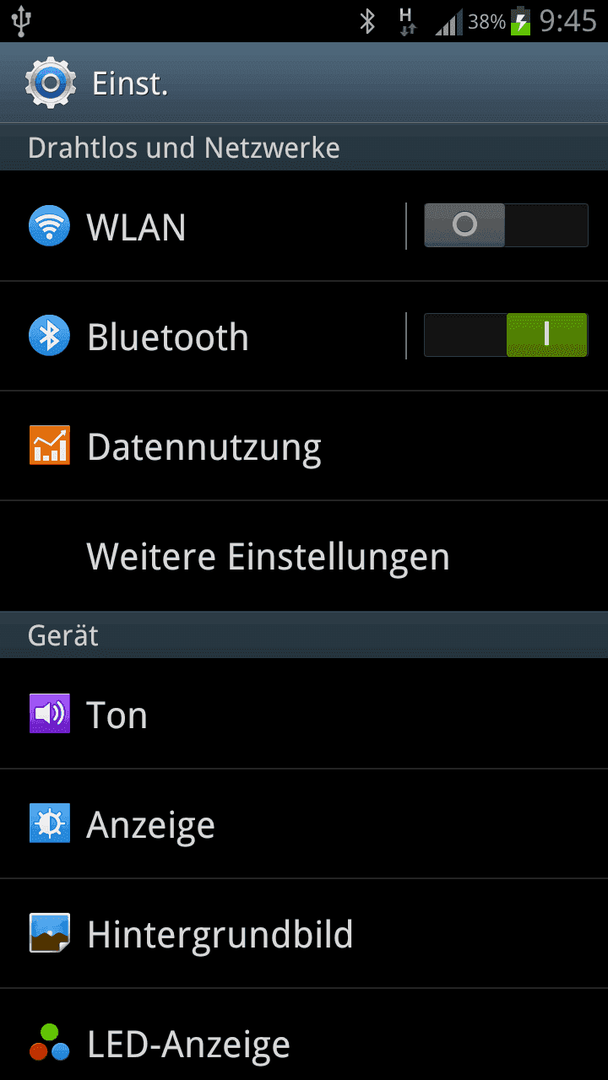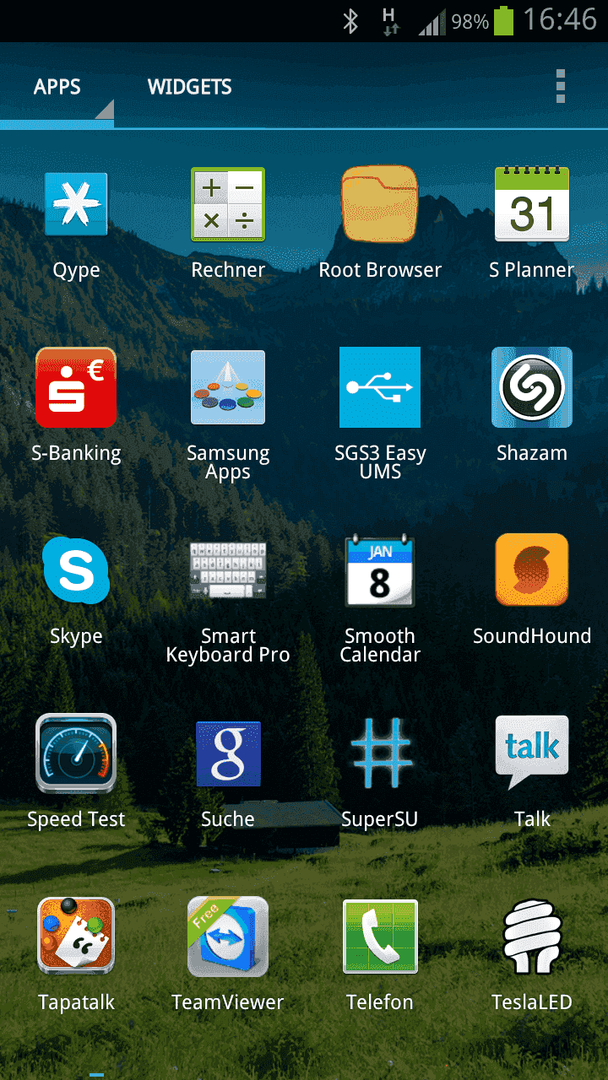
Schriftart (~Font) ändern
Ich erkenne dort keinen Unterschied.
Zwischen dem StockFont & dem Font.
Oder Täusche ich mich etwa?
Ich sehe auch keinen Unterschied.:confused:
Zumal das andere was angeboten wird (CheckROM) viel hübscher ist ^^
Was meinst Du mit "das andere"?
Aber ob hübscher oder nicht ist ja bekanntlich Geschmackssache. :flapper:
Es ist schon ein Unterschied zur Stock-Font, mir gefällt sie jedenfalls besser.
Hab nochmal ein Screenshot vom Appdrawer gemacht, vielleicht sieht man es da besser.
Sieht deutlich besser aus als die originalen Schriften.Intalliert und zufrieden ;)
Finde sie optisch auch ein wenig besser.
Ebenfalls installiert - sieht super aus! Vielen Dank für diesen heißen Tipp. :)
Na wenn sie alle hier so schwärmen, dann werde ich das auch mal ausprobieren. :flapper:
Da bleib ich dann doch besser meiner Sony Sketch Font treu.... :flapper:
Sieht schon sehr nice aus.
Läuft perfekt auf stockrom
Ich habe bei meinem LG GW620 die Schriftgröße für die meisten Apps mit einer App aus dem Android-Market (Google-Play) ändern können:
Big Font (change font size)
Funktioniert bislang super und ohne root-Beeinflussung. Bin echt zufrieden!
Wie kann ich im Sensation XL die System-Schriftart ändern?
Ich glaube du brauchst Root Acess
Bei meinem Galaxy s gibt's da ein Menü wo man mehrere zur Auswahl hat.
seit 2 Tagen les ich mich ein bisschen hier durch und suche danach,
wie man die Schriftart ändern kann,
ich hab das bei vielen schon gesehen (die hatten ein Samsung Galaxy) die sind einfach auf Einstellungen -> Anzeige -> Display -> Schriftart
bei mir und meinem HTC Desire geht das aber nicht,
Hat jemand einen Tipp für Apps oder wie man ohne Root die Schriftart ändern kann?
Lade dir mal im google play store fontomizer sp runter. Da gibt es verschiedene schriftarten, die kannst du dir dann downloaden und auswählen :)
Ohne root...... könnte problematisch werden^^